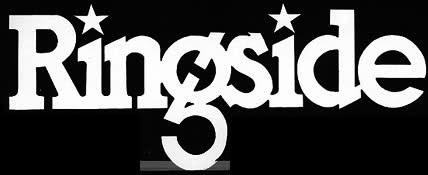
Denke mal daran, dass nicht alles eine Ausgangstypo haben muss, sondern »handgemacht« sein kann … also mit Bleistift auf dem Papier skizziert und dann umgesetzt. Das gibt’s.